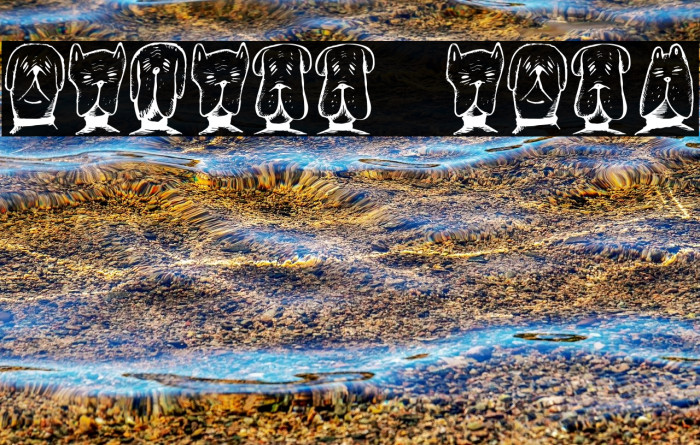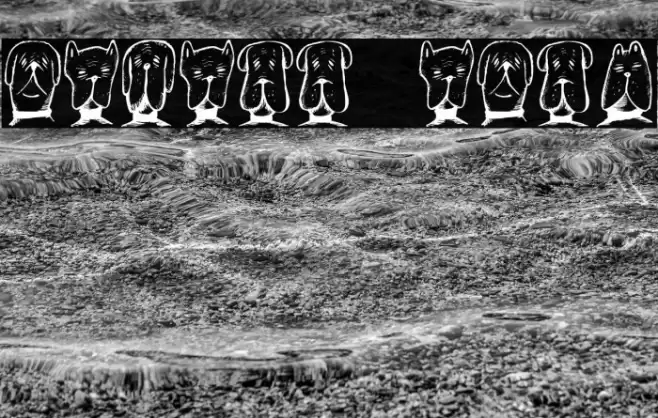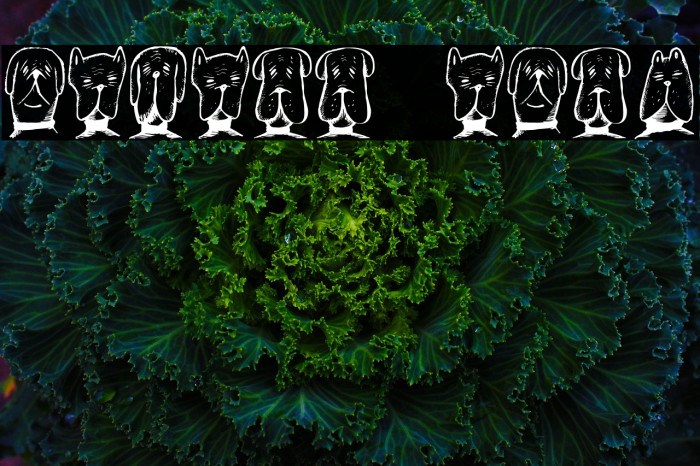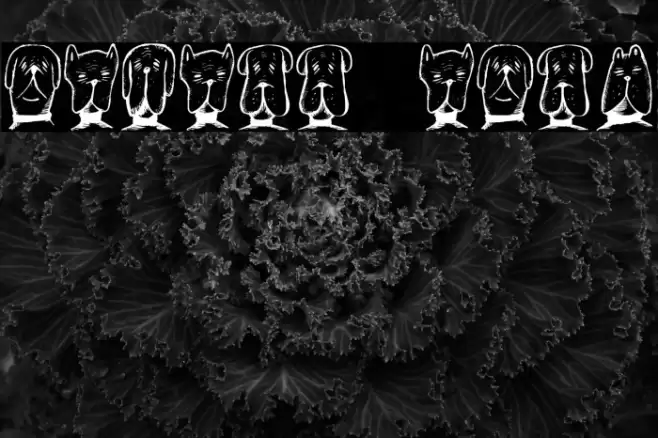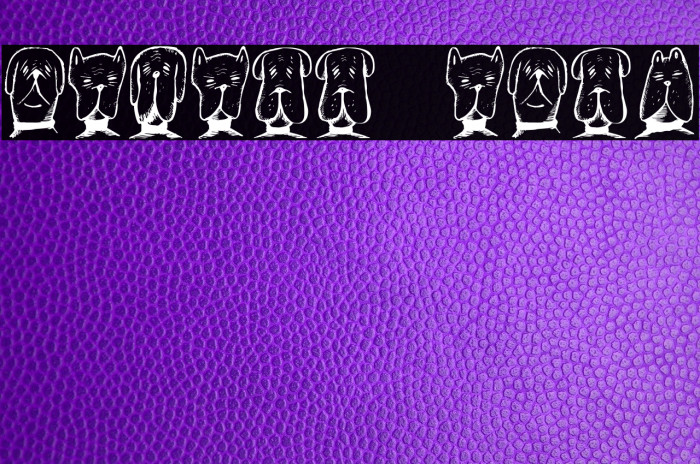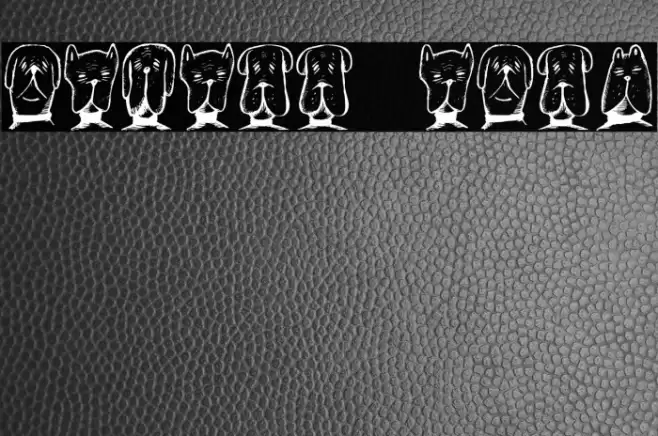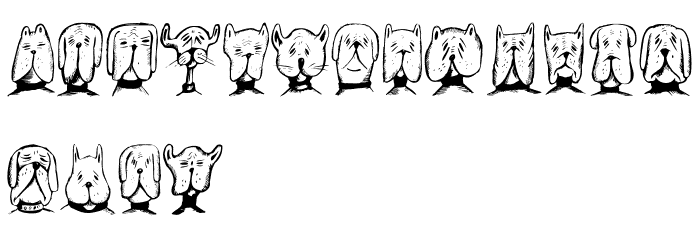
Gebell Regular Font
| Estilo geral | Whimsical, Playful |
| Caso de uso | Logos, Posters, Children's Books |
| Projetos propostos | Ideal for children's books, playful branding, greeting cards, and creative posters. |